무료로 제공되는 다양한 한글 글씨체를 활용하면, 문서 작업이나 디자인 프로젝트의 퀄리티를 크게 높일 수 있습니다. 이 글에서는 인기 있는 한글글씨체를 다운로드할 수 있는 사이트와 활용 팁을 소개합니다.
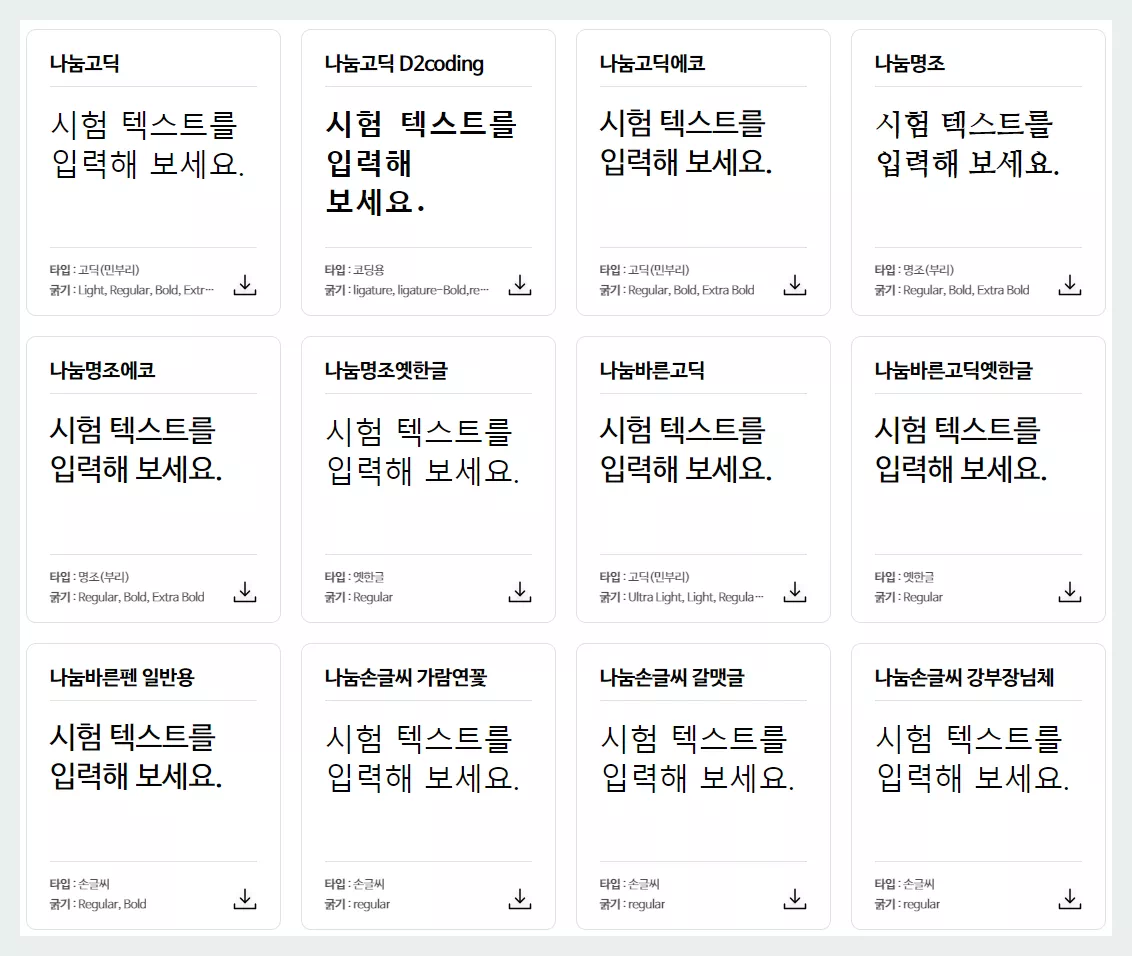
무료 한글글씨체 다운로드 사이트 소개
네이버 한글한글아름답게
네이버에서 운영하는 한글 글씨체 배포 프로젝트입니다. 대표적인 서체로는 나눔고딕, 나눔명조, 마루부리, 클로바 나눔손글씨 등이 있으며, 총 150여 종의 폰트를 무료로 다운로드할 수 있습니다. 개인 및 상업적 용도로 모두 사용할 수 있는 점이 큰 장점입니다.
- 추천 활용: 발표자료, 브랜딩 문서
눈누 (Noonnu)
눈누는 상업적 사용이 가능한 한글 무료 폰트를 모아둔 사이트입니다. 필터 기능을 통해 폰트 스타일, 두께, 사용 용도 등을 쉽게 검색할 수 있어 디자이너와 콘텐츠 제작자에게 유용합니다.
- 추천 활용: 웹디자인, 소셜미디어 콘텐츠
구글 폰트 라이브러리
구글 폰트는 글로벌 사용자를 위한 다양한 무료 서체를 제공합니다. 한글 폰트로는 Noto Sans KR과 Noto Serif KR이 대표적이며, 심플하면서도 다양한 굵기를 제공해 가독성이 우수합니다.
- 추천 활용: 웹사이트, 애플리케이션 인터페이스
한국저작권위원회 공유마당
저작권 걱정 없이 사용할 수 있는 공공 서체를 제공하는 사이트입니다. 공공기관 및 개인이 배포한 다양한 폰트를 확인할 수 있으며, 상업적 이용도 가능합니다.
- 추천 활용: 출판물, 홍보 자료
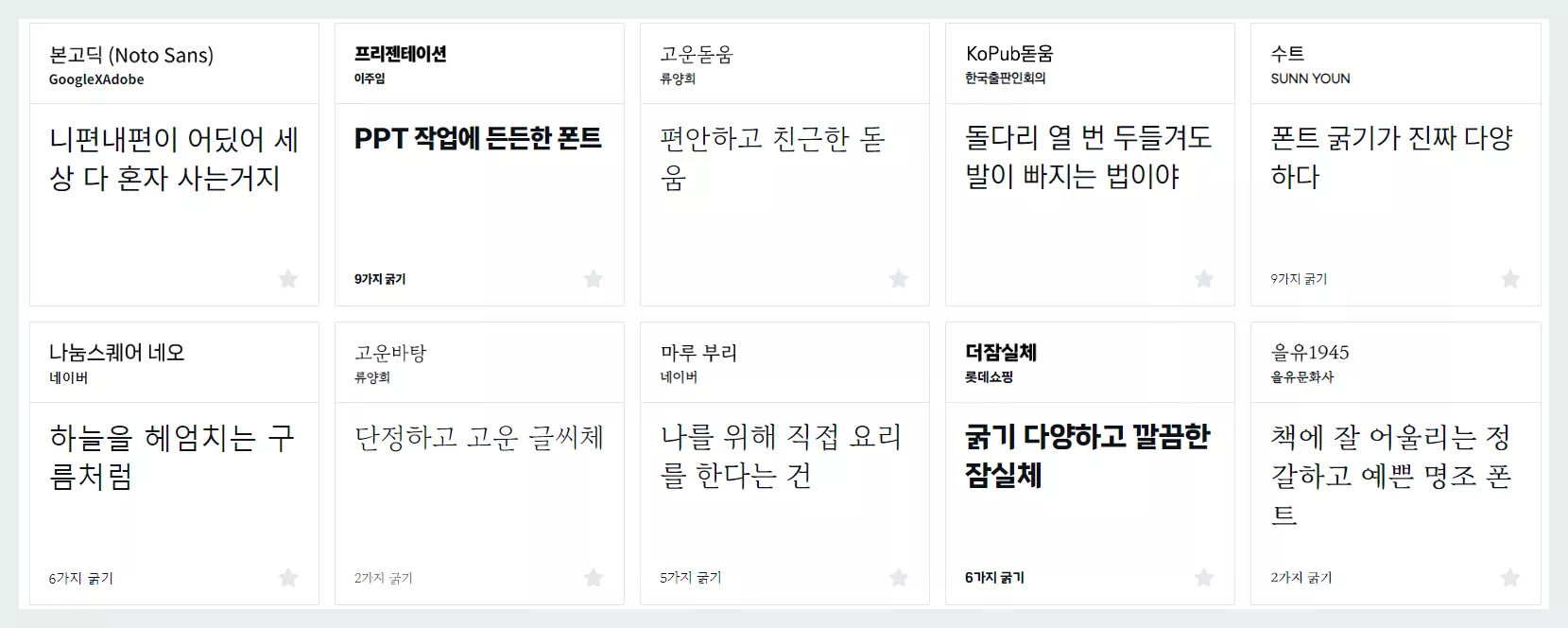
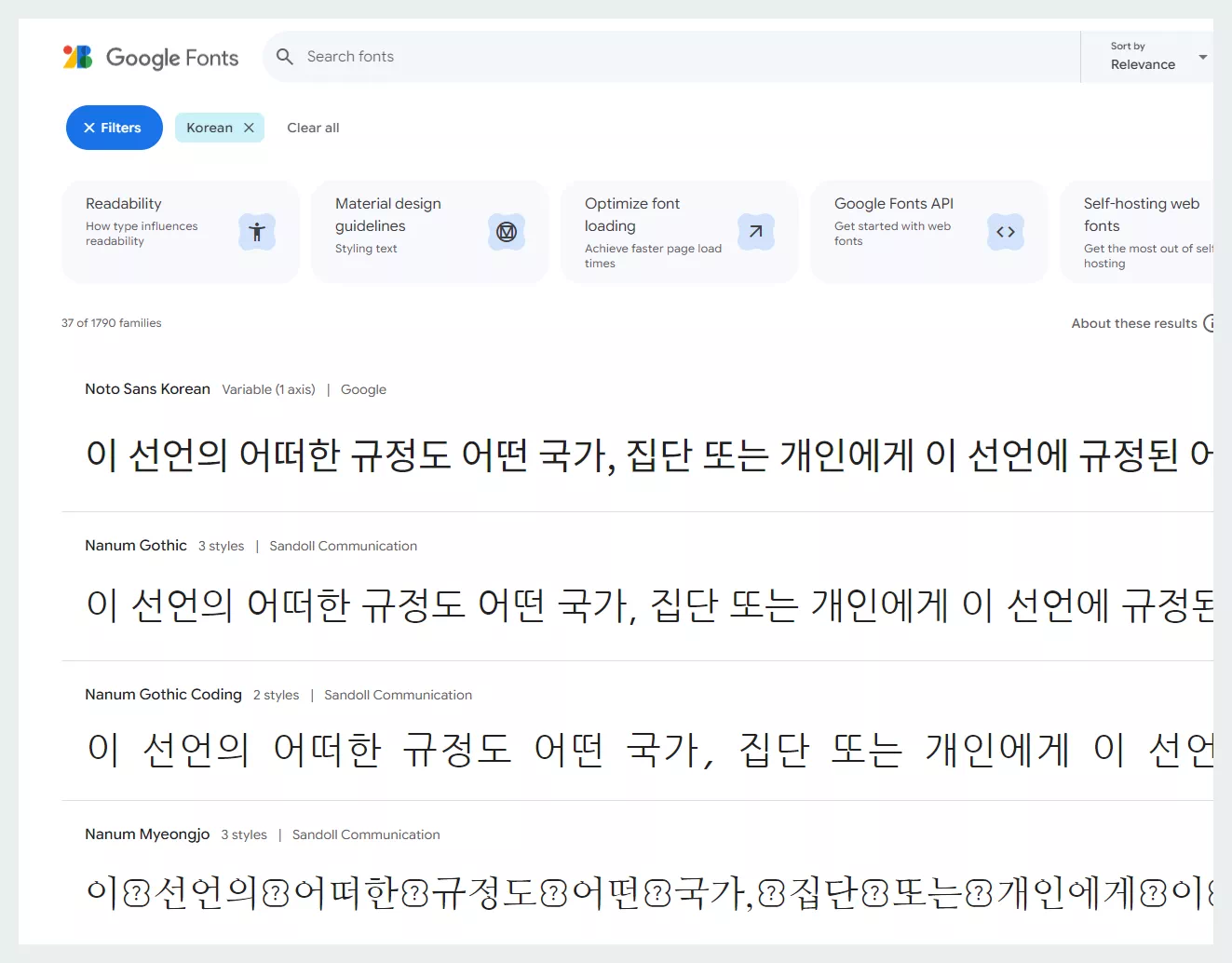
타겟 독자별 추천 서체
20~30대: 트렌디한 디자인을 선호하는 사용자
- 추천 서체: 눈누에서 제공하는 감각적인 폰트, Noto Sans KR
- 활용 사례: SNS 콘텐츠, 로고 디자인
40~50대: 전통적인 느낌을 선호하는 사용자
- 추천 서체: 나눔명조, KoPub 바탕체
- 활용 사례: 출판물, 공문서
디자이너 및 크리에이터
- 추천 서체: 눈누 및 산돌구름의 개성 있는 폰트
- 활용 사례: 브랜딩, 웹디자인
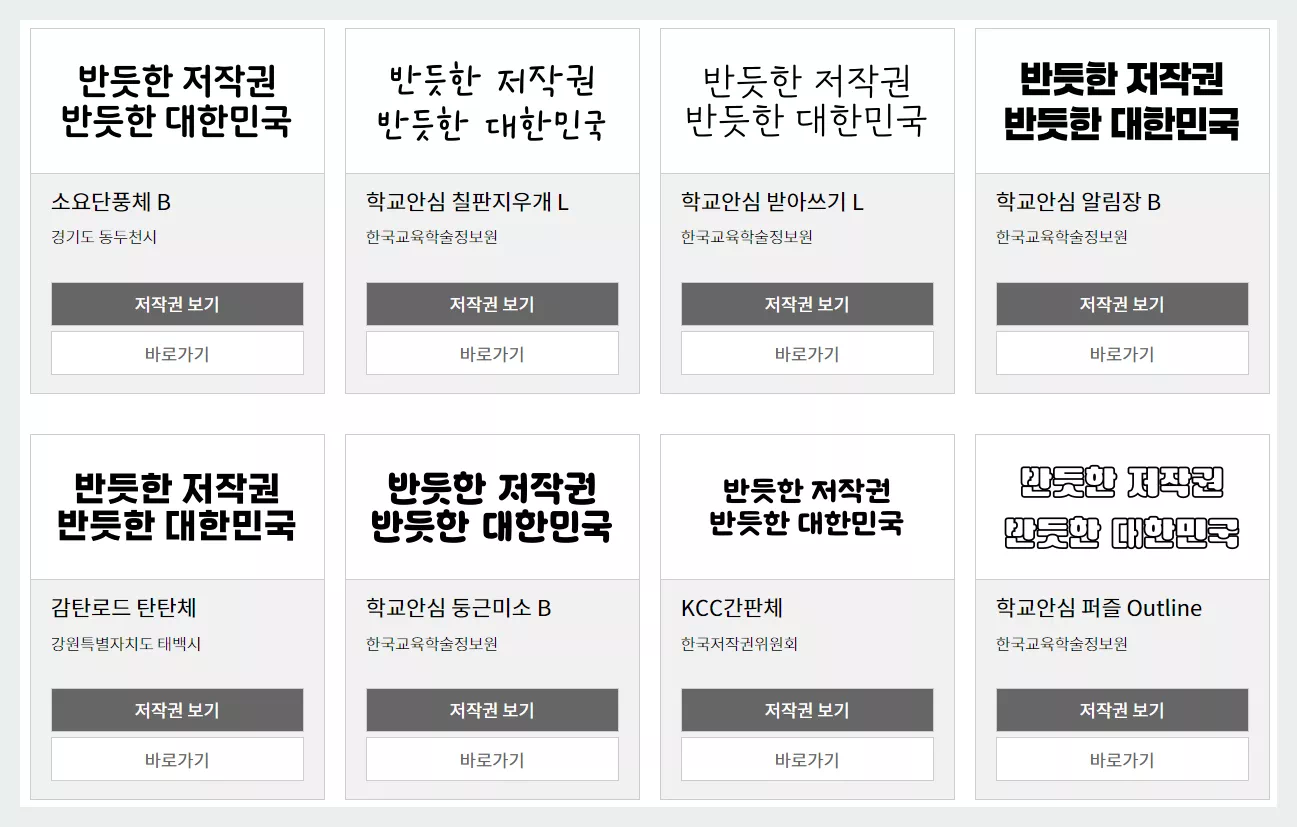
한글글씨체 다운은 문서 작업, 디자인 프로젝트 등 다양한 분야에서 필수적입니다. 위의 정보를 참고해 자신에게 맞는 서체를 다운로드하고 활용해 보세요!